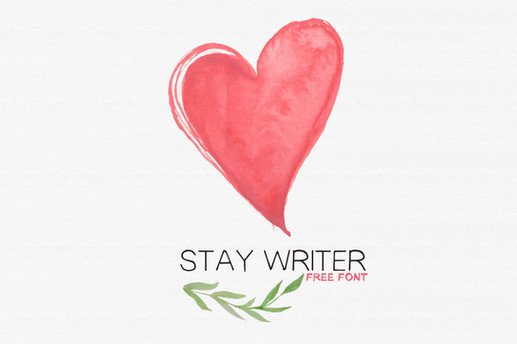
DOWNLOAD HERE ¡Hola! Al fin subo algo a mi cuenta. Como soy fan de las fonts y tengo una carpeta con miles de ellas de diferentes tamaños y estilos, quise compartir 6 fonts tipo caligrafía (que me gustan mucho y uso para muchos proyectos escolares). Asique espero que les gusten o les sirvan. / Hello! I finally upload something to my account. As I am a big fan of the fonts and I have a folder with thousands of them of different sizes and styles, I wanted to share 6 calligraphy fonts (which I like a lot and use for many school projects). So I hope you like them or serve them. CONTIENE / CONTAINS : 6 fonts tipo caligrafía / 6 calligraphy fonts. Espero que les sea útil. / I hope you find it useful. © 2013- 2023 GregTutorials - All rights reserved.